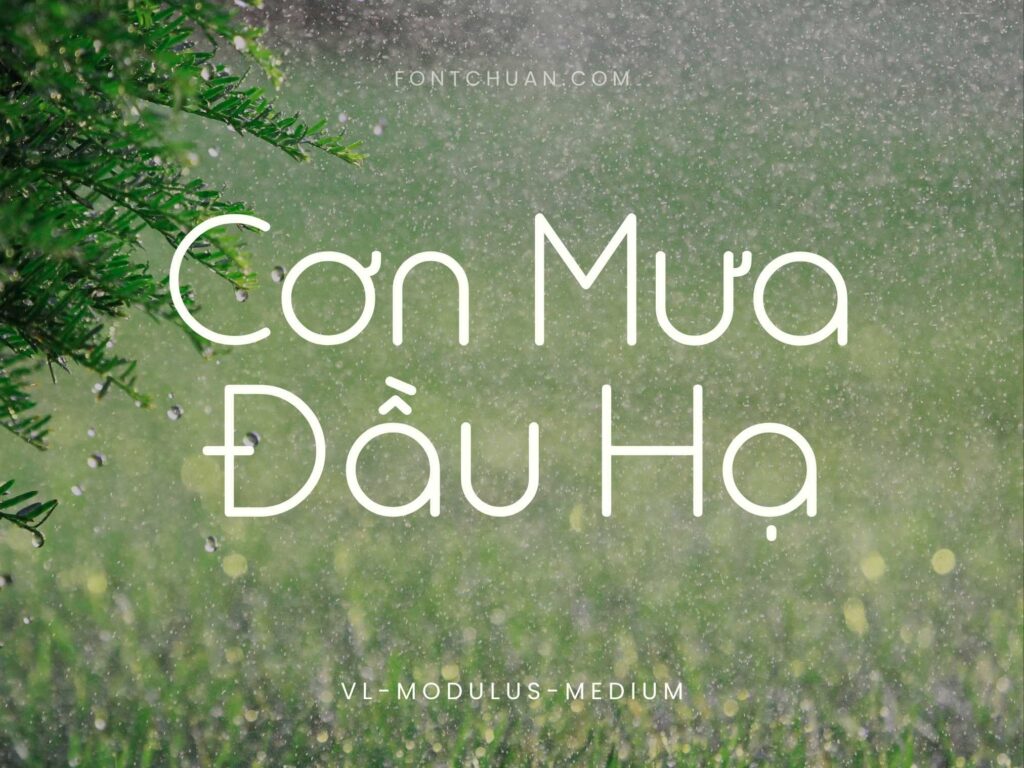
Font VL Modulus Medium Việt Hóa
VL-MODULUS-MEDIUM là một phông chữ sans-serif hiện đại, mang phong cách tối giản và sạch sẽ. Với các đường nét tròn trịa và mượt mà, phông chữ này tạo cảm giác tinh tế và chuyên nghiệp cho các thiết kế. VL-MODULUS-MEDIUM đã được Việt hóa bởi Việt Linh, hỗ trợ đầy đủ các ký tự tiếng Việt, giúp người dùng dễ dàng áp dụng trong nhiều dự án sáng tạo. Phông chữ này được thành viên Font Chuẩn sưu tầm và đăng tải nhằm phục vụ nhu cầu thiết kế đa dạng.
Với thiết kế rõ ràng và linh hoạt, VL-MODULUS-MEDIUM phù hợp cho các ứng dụng như tiêu đề, văn bản dài, thiết kế logo và các ấn phẩm in ấn. Trong lĩnh vực sự kiện, phông chữ này có thể được sử dụng trong các dịp như lễ hội, thiệp cưới, sinh nhật và các sự kiện văn hóa. Ngoài ra, VL-MODULUS-MEDIUM cũng thích hợp cho các ngành nghề như quảng cáo, giáo dục, công nghệ và bất động sản.